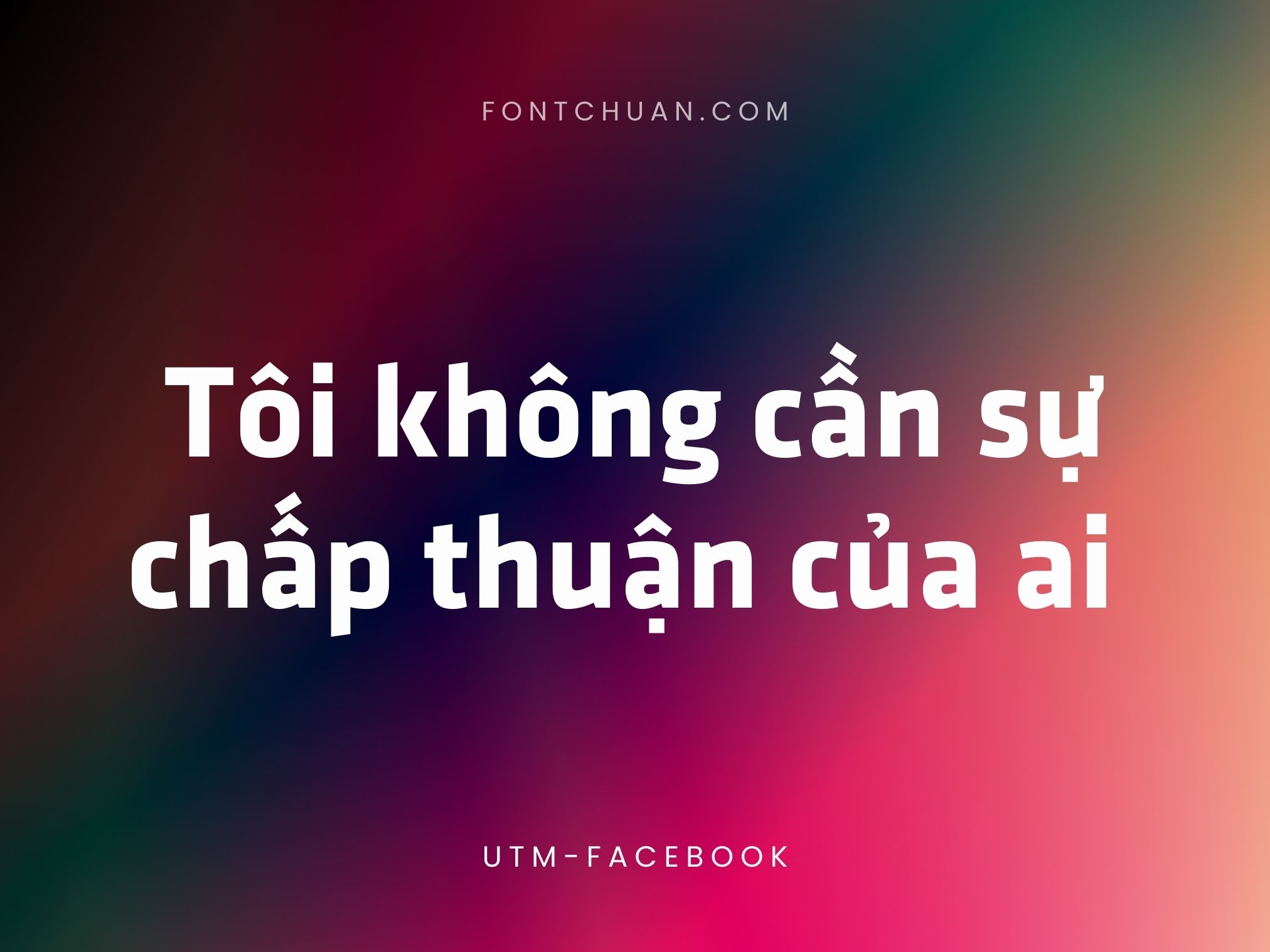
UTM Facebook là phiên bản Việt hóa của font chữ sử dụng trong logo của Facebook, một kiểu chữ sans-serif hiện đại với thiết kế đơn giản và dễ đọc. Font này nổi bật với các ký tự có đường nét gọn gàng, tạo cảm giác thân thiện và chuyên nghiệp. Phiên bản Việt hóa đã được thực hiện bởi Công ty TNHH Vitoen, hỗ trợ đầy đủ tiếng Việt cùng hơn 100 ngôn ngữ khác. Đây là một trong những font được cộng đồng thiết kế sưu tầm và chọn lọc nhằm đáp ứng nhu cầu đa dạng trong thiết kế.
UTM Facebook có cấu trúc chữ với các nét thẳng và độ dày đồng đều, tạo nên sự rõ ràng và dễ đọc. Font này phù hợp cho các ứng dụng như thiết kế tiêu đề, logo, biển hiệu và các ấn phẩm in ấn yêu cầu sự hiện đại và tối giản. Các ngành nghề như quảng cáo, giáo dục, công nghệ và bất động sản có thể tận dụng UTM Facebook để tạo điểm nhấn độc đáo trong thiết kế.